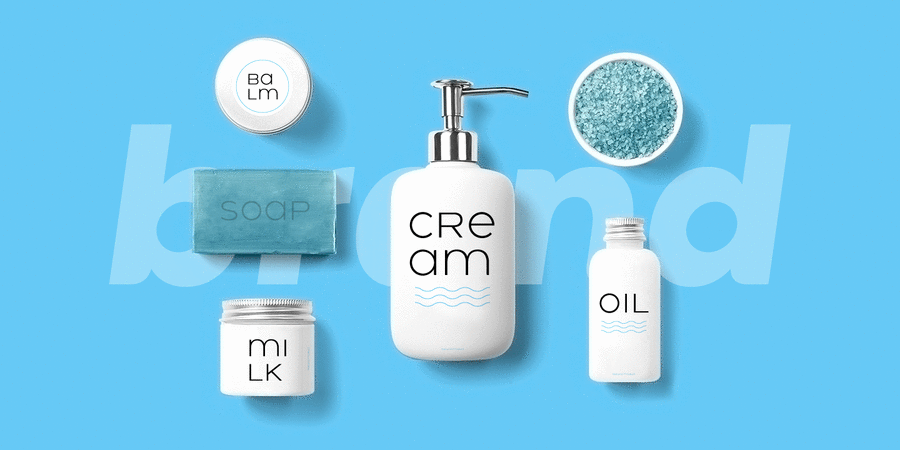
Стиль гарнітури:
12 накреслень
Опис гарнітури HolgadaЦе геометричний гротеск з витонченими закругленими закінченнями, які забезпечують м'який і доброзичливий вигляд. Прості форми цього шрифту роблять його придатним для будь-якого типу проектів, текстів будь-якої довжини та розміру. Завдяки чіткості й розбірливості Holgada можна використовувати в текстових смугах маленького кеглю, у великих заголовках і в усьому, що між ними. Закруглені закінчення додають особливу м'якість при використанні в логотипах, вивісках і назвах. Holgada складається з 12 накреслень, що містять капітель і знаки багатьох мов латинки й кирилиці. Шрифт розробив Пабло Балселлс у 2020 році.
Особливості сімейства шрифтів HolgadaХіт десятиліття:
Асоціації з сімейством шрифтів HolgadaОсобистість і характер гарнітури:
делікатний, чистий, легкий, прохолодний, модний, тонкий, сучасний, лаконічний, якісний, невагомий, прозорий, інтимний, крихкий, ніжний, повітряний, скляний, гострий, дротяний, худий, круглий, спокійний, свіжий, ясний, рівний, мирний, міський, формальний, зрозумілий, Простий, точний, непомітний, гладенький, щедрий, добрий, привітний, дитячий, милий, пишний, доброзичливий, затишний, приємний, пластмасовий, сімейний, смачний, комфортний, бадьорий, домашній, симпатичний, здоровий, зручний, помітний, яскравий, хіпстерський, чесний, екологічний, довірчий, теплий, апетитний, красивий, характерний, акуратний, соковитий, стиглий, літній, няшний, ефектний, культурний, добірний, ввічливий
краса, туалетна вода, косметика, мода, дієта, гігієна, чистота, парфумерія, лосьйон, шампунь, перукарня, дизайн, АСМР, Інстаграм, здоров'я, Місто, навігація, ліки, одяг, взуття, інтер'єр, йога, небо, вода, прилад, технології, автобус, торгівля, їжа, молоко, дитяче харчування, родина, гра, сік, дитяча книжка, готель, дім, аптека, транспорт, продукти, розваги, свято, кетчуп, жуйка, підгузок, ресторан, фарба, магазин, чіпси, фрукти, мармелад Гарнітура асоціюється з віком: